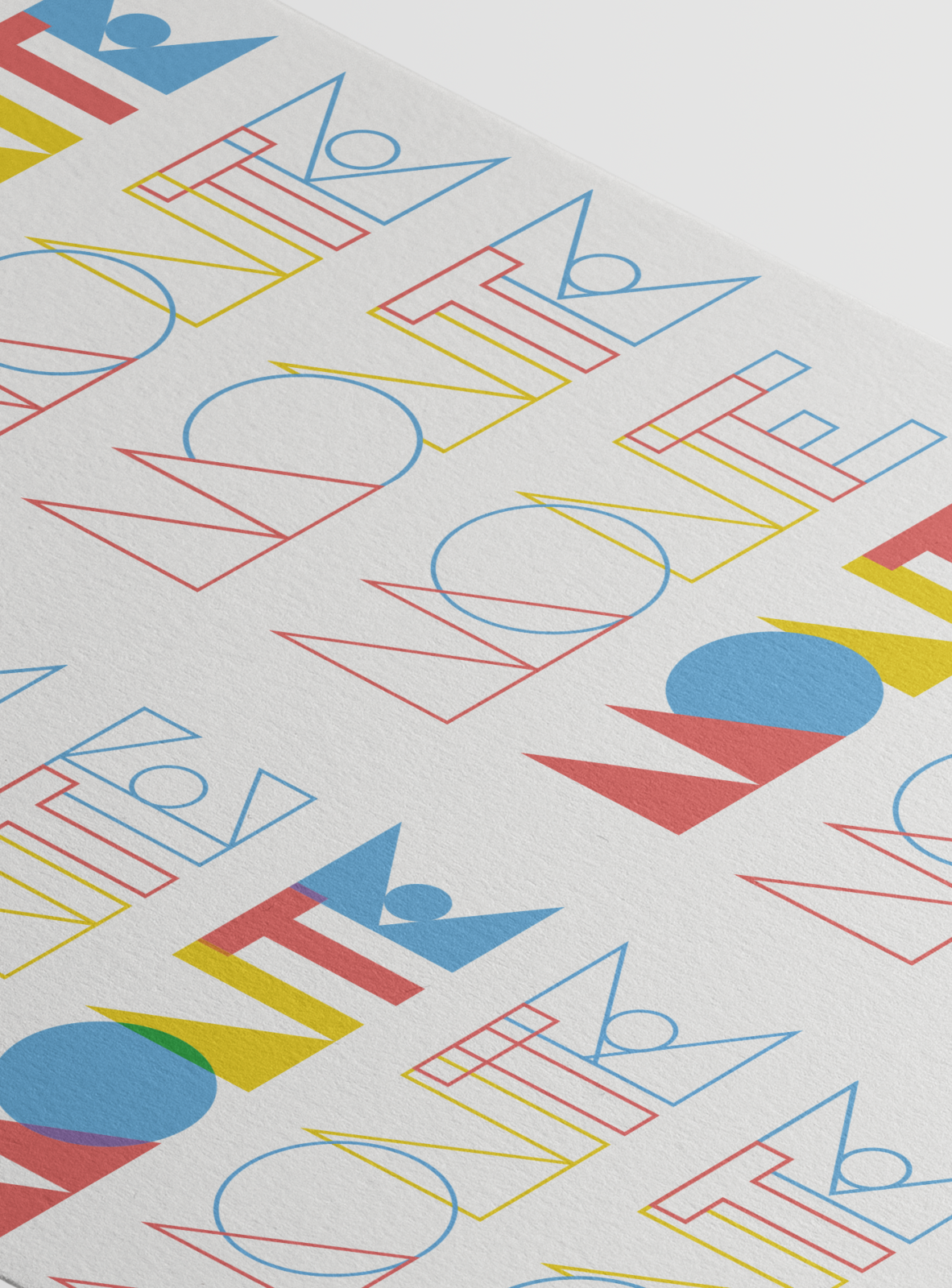
Aus dem Kreis, Rechteck und Dreieck wirkt das Logo modular und stabil wie Bauklötze. Durch die farbige Kontur dennoch leicht und frei. Sie geben einen gesteckten Rahmen vor, in welchem sich frei und offen bewegt werden kann, der veränderbar ist. Das Rot, Blau und Gelb ergibt sich aus den Grundfarben des Farbkreises.
In der Montessoripädagogik werden Materialien lernunterstützend eingesetzt. Dabei sind die Materialien hochwertig, ansprechend und harmonisch gestaltet. Sie laden das Kind förmlich ein, sie zu berühren, zu verändern und sich mit ihnen zu beschäftigen. Es werden Grundfarben genutzt, um Kindern eine zusätzliche Unterstützung in der Auseinandersetzung mit den Lernmaterialien zu bieten. Ebenso orientiert sich die Einfachheit und Wiederholung in den geometrischen Grundformen, in denen die Materialien gestaltet sind.
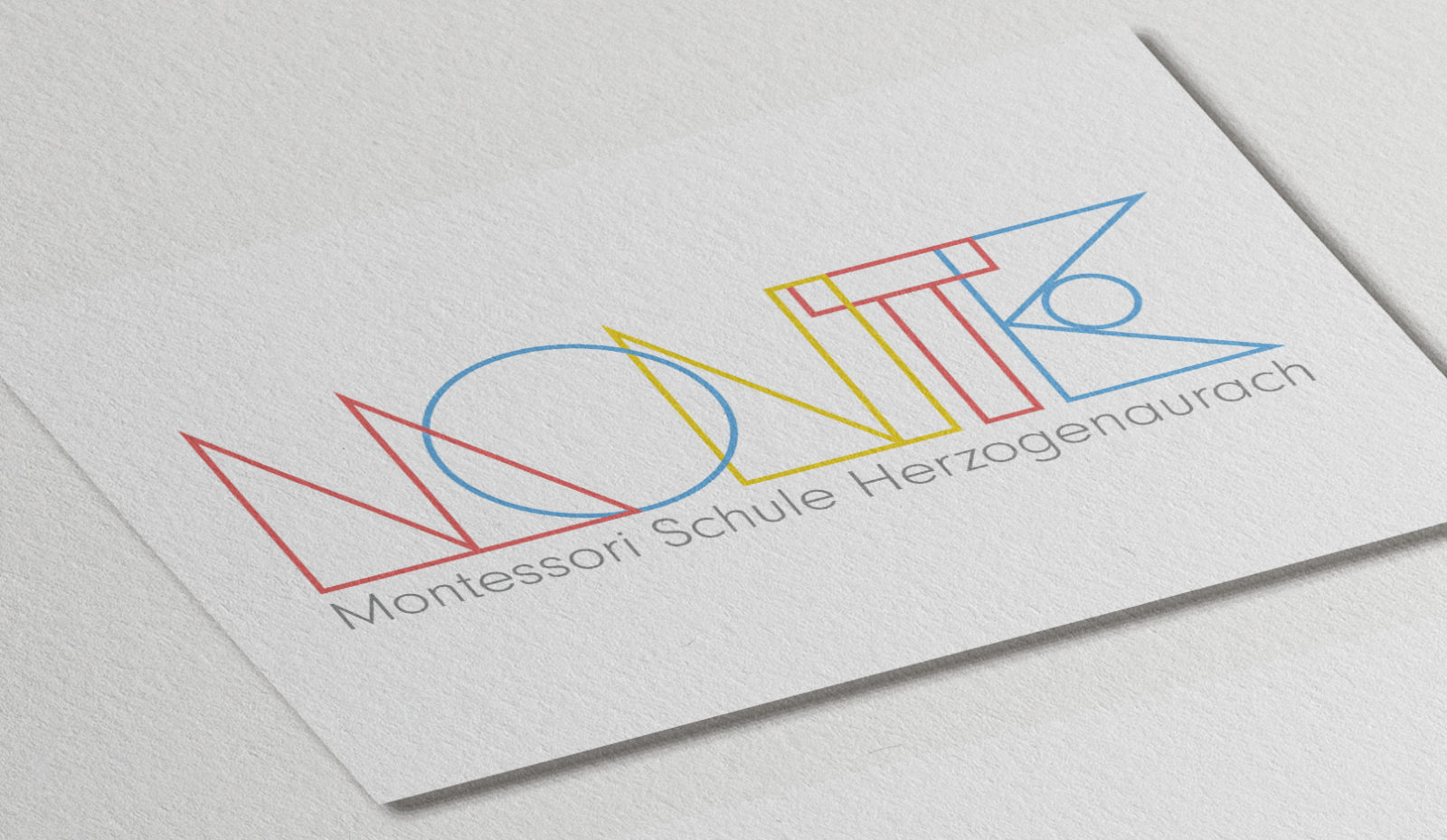
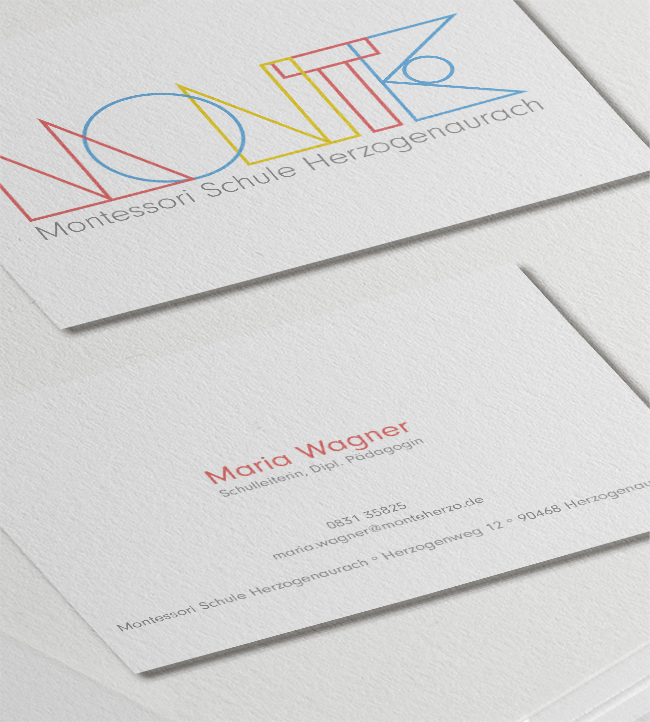
MONTE